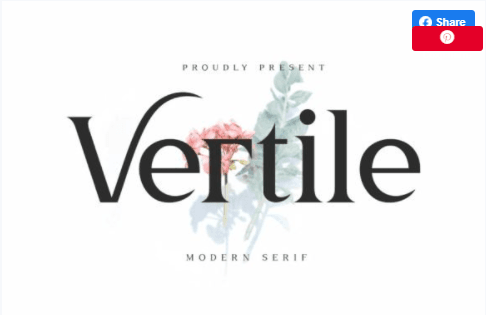
Vertile Font
Vertile - это элегантный жирный шрифт с засечками. Он отличается плавными изгибами и идеально подходит для модного брендинга или редакционных дизайнов. Добавьте его уверенно в свои проекты, и результат вам понравится.